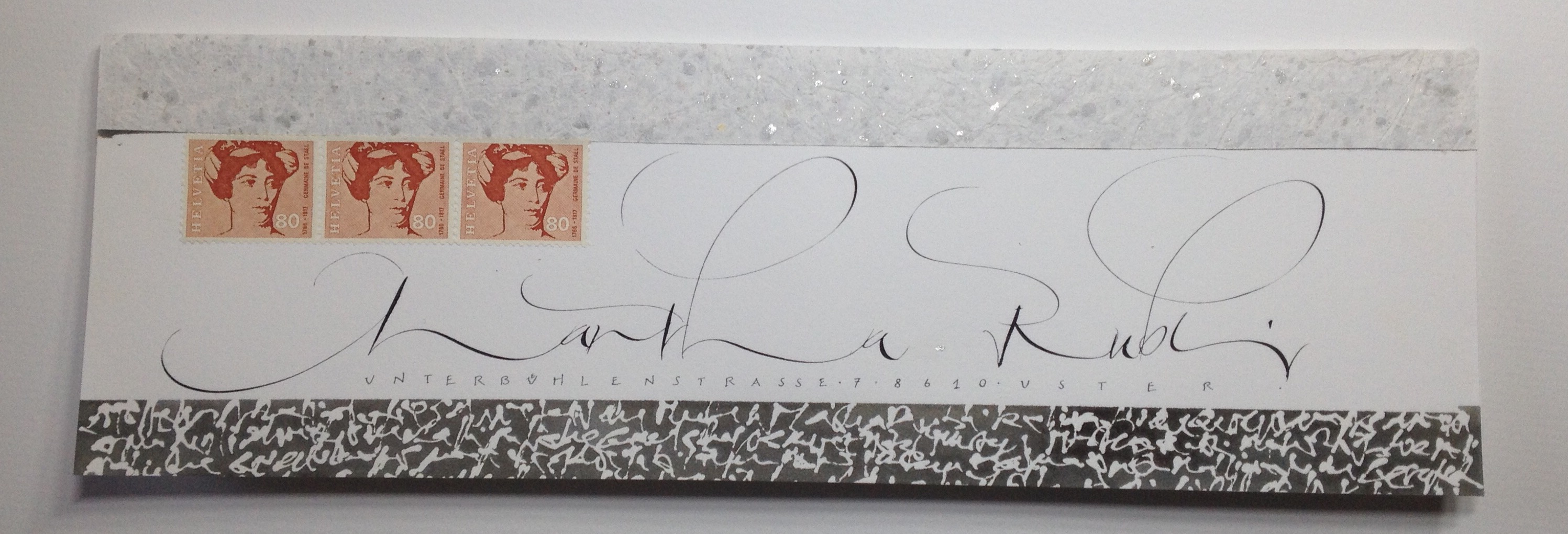
Kalligrafie ist die Kunst des Schönschreibens. In unserer Zeit der schnellen Nachrichten lebt die Kalligrafie von der Achtsamkeit auf einen Strich, dem Geräusch der Feder auf rauem Papier, dem Duft einer feinen Kräutertinte… im Hier und Jetzt. Herzlich willkommen!
Möchten Sie die moderne Schnürlischrift mit der Spitzfeder schreiben lernen? Oder in eine klassische Schrift einsteigen? Was es alles zu lernen gibt finden Sie hier.
Siegerpreis: Ich bin überwältigt und überglücklich: Mein Couvert wurde an der GV der
Schweizerischen Kalligraphischen Gesellschaft vom 25. Oktober 2015 zum Siegercouvert 2015 gewählt! Was für eine Ehre, was für eine Freude! Danke!!! Auch an Martha Rubli für die Erlaubnis, das Couvert hier abzubilden!